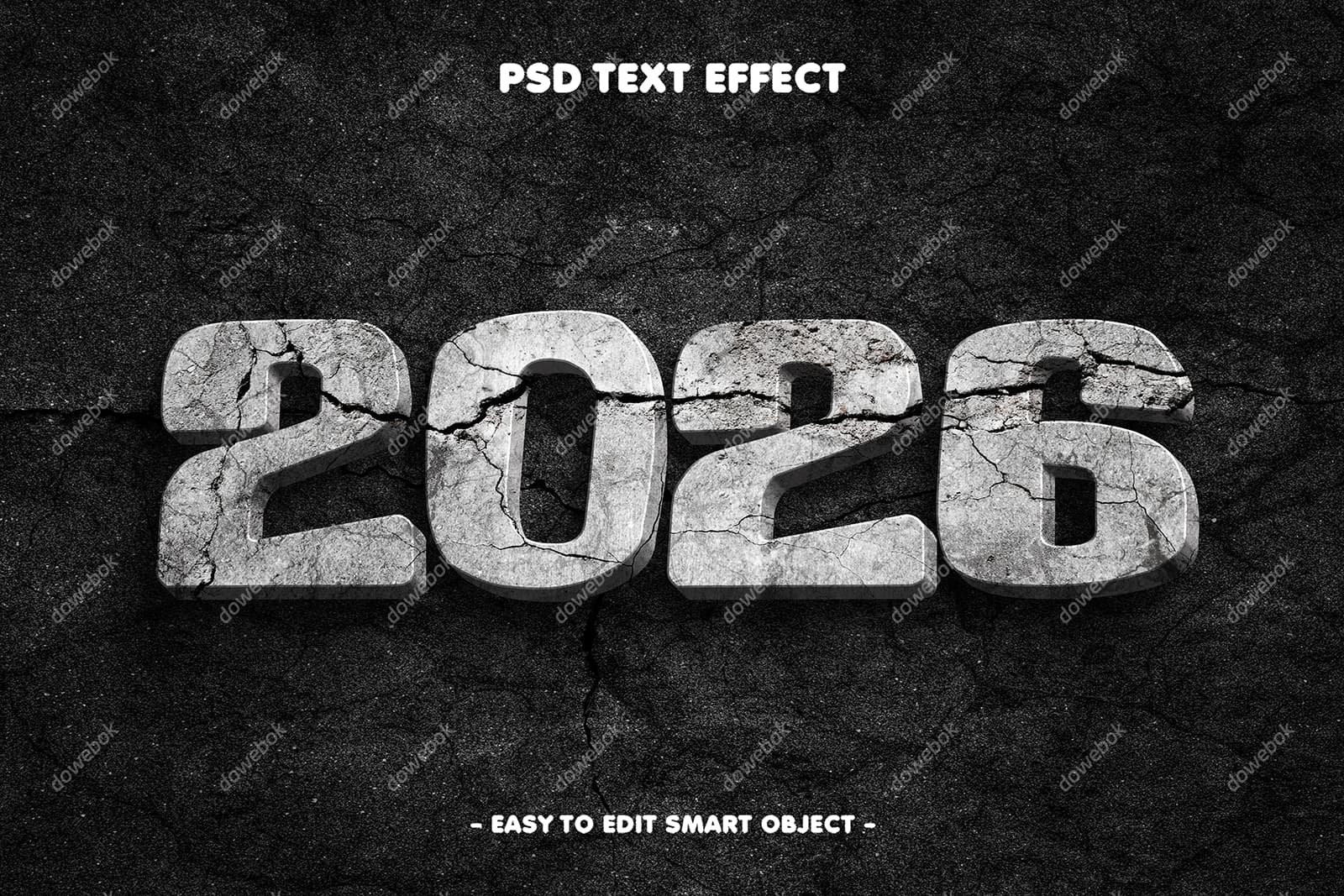
这是一款由破裂的石材数字设计的 2026 新年快乐 PSD 素材,黑灰裂纹背景上,“2026” 以仿破损石材的立体字呈现,裂纹纹理强化了粗粝的工业废墟质感。顶部标 “PSD TEXT EFFECT”,底部注其为可编辑素材。整体黑白配色既显冷峻硬核,又借石材破损效果突出视觉张力,既点明字体效果的创意属性,也适配暗黑工业风的创意海报、装饰物料等场景。